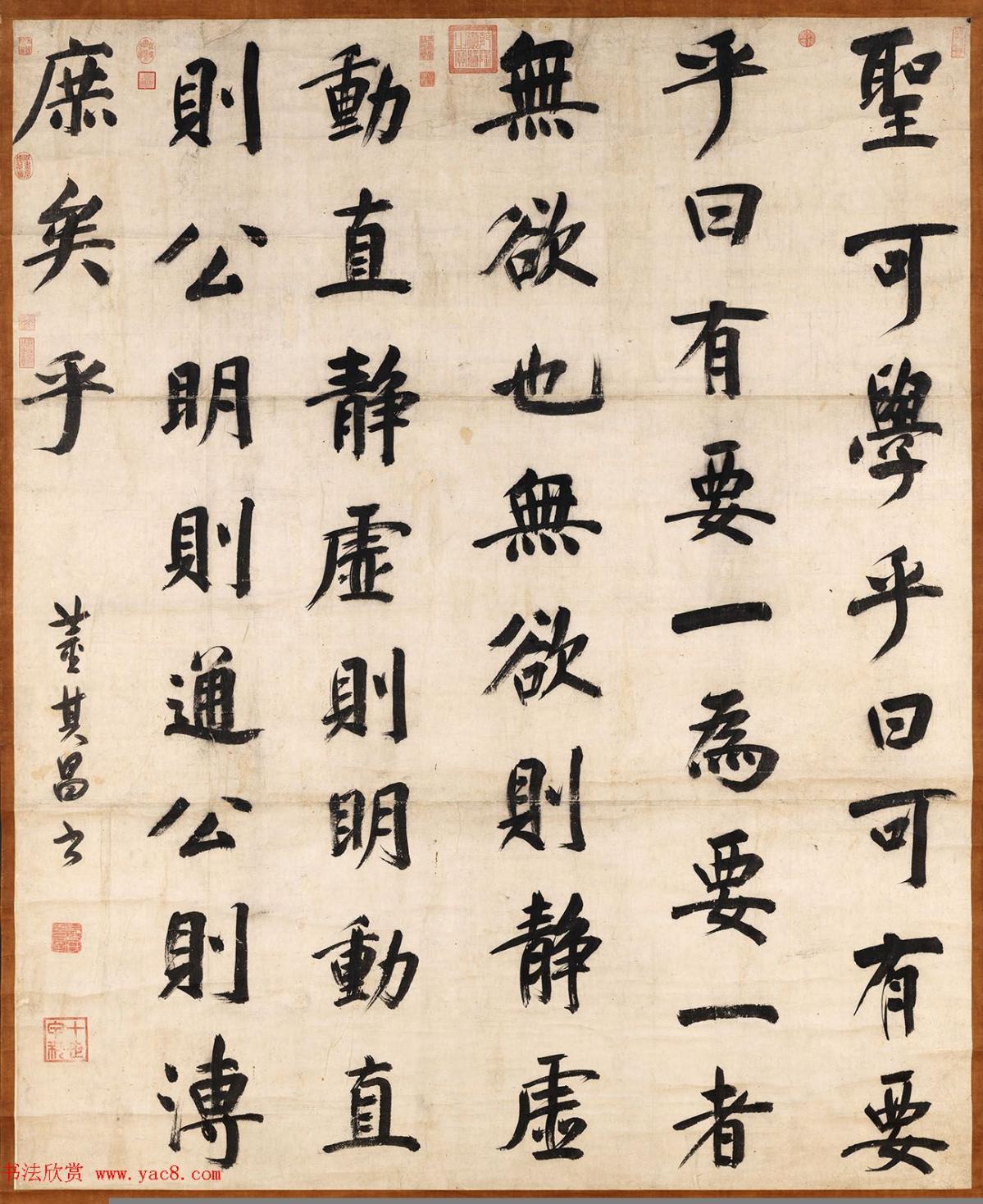
明代董其昌楷書賞析《周子通書》軸,紙本189.4×154.5公分,台北故宮博物院藏。董其昌(1555-1636),工書畫,精鑑賞。晚明以來,其書畫創作、美學思想、藝術史觀不斷發揮影響力,至今未歇。
此軸約作於1611年,書周敦頤語,論人如何學以至聖。通篇揉合歐陽詢、顏真卿的楷書風格,線條圓厚,字形端正而略顯修長。濃墨與飛白的對比表現出提按的韻律感,並使人感到筆法的灑脫與豪邁。